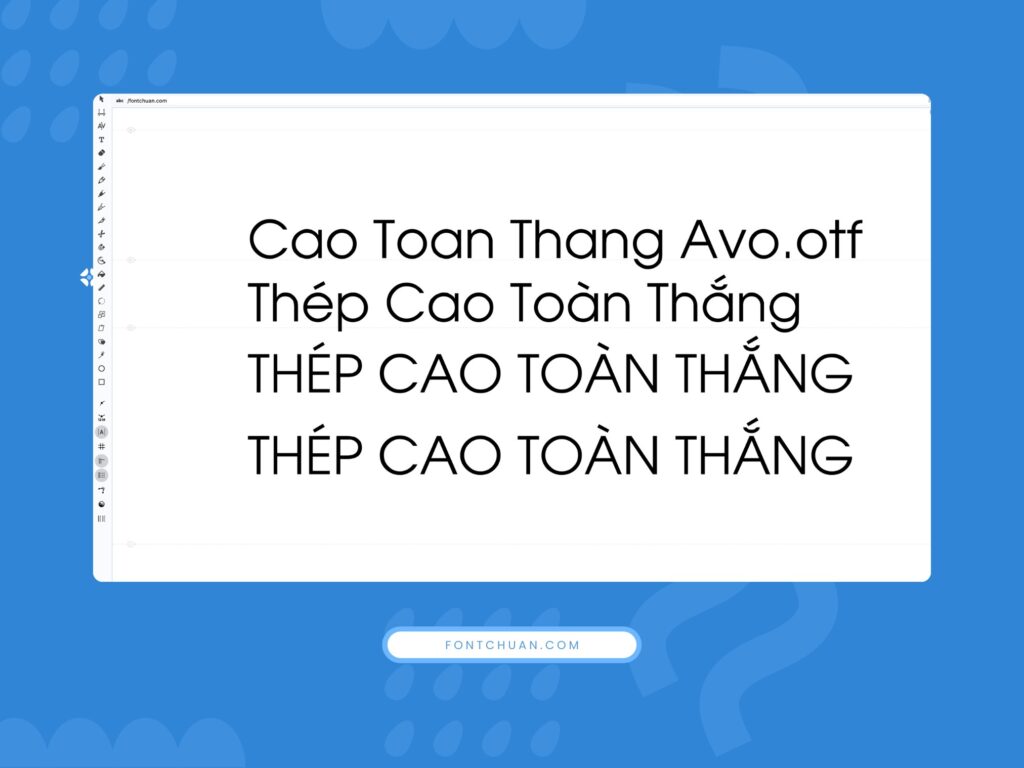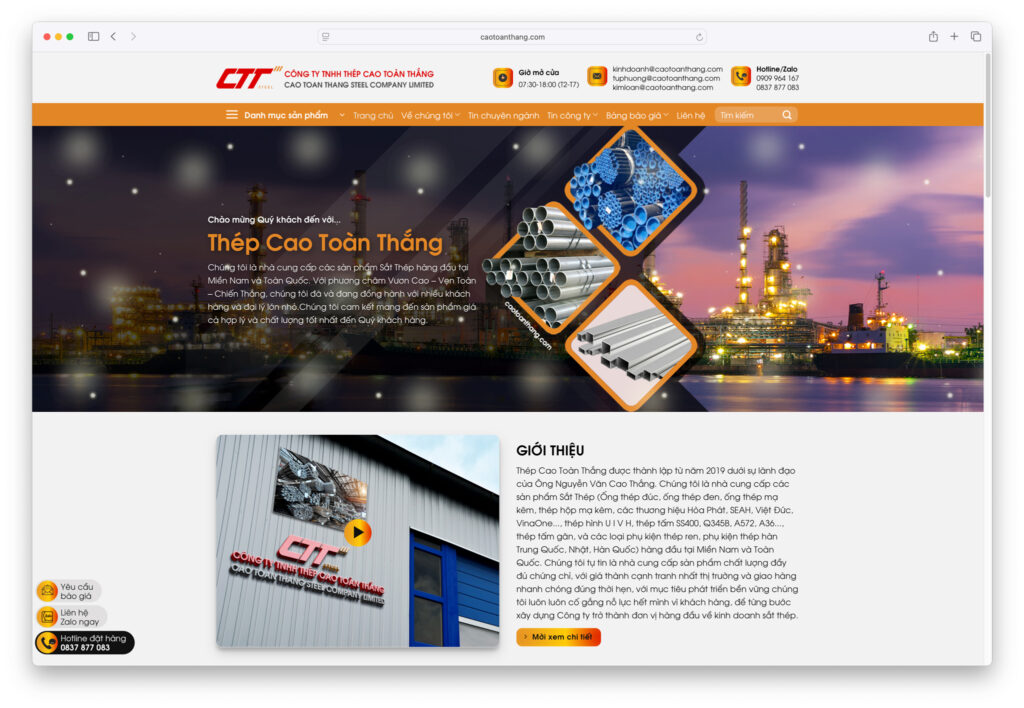
Thép Cao Toàn Thắng dẫn đầu “ngành thép” với Font riêng
Thép Cao Toàn Thắng dẫn đầu "ngành thép" với Font riêng
Thép Cao Toàn Thắng là một trong những đối tác và khách hàng chiến lược của Font Chuẩn. Một trong những doanh nghiệp uy tín hàng đầu trong lĩnh vực cung cấp sắt thép, đặc biệt là sản phẩm ống thép đúc tại Việt Nam. Với hệ thống sản phẩm đa dạng, chất lượng kiểm định rõ ràng, giá cả cạnh tranh và dịch vụ tận tâm, công ty đã xây dựng được mạng lưới khách hàng rộng khắp trên toàn quốc. Không chỉ chú trọng đến năng lực phân phối, Cao Toàn Thắng còn đầu tư bài bản vào hình ảnh thương hiệu để tạo nên sự khác biệt và tăng cường độ nhận diện.
Thách thức nhận diện thương hiệu trong ngành sắt thép
Ngành công nghiệp sắt thép mang tính kỹ thuật cao, với nhiều sản phẩm có hình thức và thông số gần giống nhau. Do đó, thương hiệu rất dễ bị đồng hóa nếu không có hệ thống nhận diện rõ ràng và nhất quán. Trong bối cảnh thị trường cạnh tranh gay gắt, việc đầu tư vào bộ nhận diện chuyên nghiệp không chỉ giúp tăng độ tin cậy mà còn tạo lợi thế rõ rệt về mặt truyền thông và tiếp cận khách hàng. Font chữ dù là một chi tiết nhỏ lại đóng vai trò trung tâm trong việc thiết kế các tài liệu, bảng hiệu, website và hệ thống bao bì sản phẩm.
Lý do chọn thiết kế font riêng tại Font Chuẩn
Thép Cao Toàn Thắng mong muốn sở hữu một kiểu chữ riêng biệt, phản ánh đúng tinh thần của ngành thép: mạnh mẽ, cứng cáp và hiện đại. Các font chữ phổ thông thường thiếu đi cá tính và không đáp ứng đủ yêu cầu về thẩm mỹ lẫn kỹ thuật của một doanh nghiệp công nghiệp. Vì vậy, việc thiết kế một bộ font chữ đẹp độc quyền là bước đi chiến lược nhằm đồng bộ hóa toàn bộ hệ thống truyền thông – từ bảng báo giá, website, bao bì đến nhãn mác thép.
Font Cao Toan Thang Avo.otf được thiết kế bởi Font Chuẩn
Font Cao Toan Thang Avo.otf ra đời
Font chữ “Cao Toan Thang Avo.otf” là sản phẩm được thiết kế riêng theo yêu cầu của doanh nghiệp. Font mang phong cách công nghiệp đặc trưng với các đường nét chắc khỏe, cấu trúc chữ hiện đại, tạo cảm giác vững chãi và đáng tin cậy. Toàn bộ hệ thống ký tự được Việt hóa đầy đủ, hỗ trợ in ấn rõ nét và trình chiếu tốt trên các nền tảng kỹ thuật số. Đây là yếu tố giúp doanh nghiệp thể hiện bản sắc riêng và dễ dàng mở rộng ứng dụng trong mọi hoạt động truyền thông.
Quy trình thiết kế và triển khai
Quá trình thiết kế font bắt đầu từ việc phân tích nhận diện thương hiệu hiện tại, ngành nghề hoạt động và mục tiêu truyền thông của doanh nghiệp. Từ đó, đội ngũ thiết kế đã phát triển các biến thể font phù hợp: cân bằng giữa yếu tố kỹ thuật và tính thẩm mỹ. Sau khi hoàn thiện, font được thử nghiệm trực tiếp trên các nền tảng thực tế như website, tài liệu nội bộ, bảng hiệu nhà máy, tem nhãn sản phẩm… trước khi chính thức đưa vào sử dụng.
Website CaoToanThang.com sử dụng Font Cao Toan Thang Avo.otf
Website CaoToanThang.com sử dụng Font Cao Toan Thang Avo.otf rất hoàn hảo
Kết quả và phản hồi tích cực
Sau khi áp dụng font “Cao Toan Thang Avo.otf” do Font Chuẩn thiết kế, bộ nhận diện của doanh nghiệp trở nên đồng bộ, chuyên nghiệp và dễ nhận diện hơn. Các tài liệu kỹ thuật, báo giá và ấn phẩm truyền thông đều trở nên rõ ràng, thẩm mỹ và nhất quán. Đối tác và khách hàng đánh giá cao sự đầu tư bài bản, từ chi tiết nhỏ nhất như kiểu chữ cho đến cách trình bày tổng thể. Đây cũng là bước đệm quan trọng giúp doanh nghiệp mở rộng quy mô và nâng cao vị thế trên thị trường.
Thiết kế font riêng không chỉ là yếu tố thẩm mỹ, mà còn là tài sản chiến lược giúp doanh nghiệp xây dựng thương hiệu mạnh mẽ và nhất quán. Với bộ font “Cao Toan Thang Avo.otf”, Thép Cao Toàn Thắng đã khẳng định vị thế tiên phong trong việc ứng dụng thiết kế vào ngành công nghiệp nặng. Đây là hướng đi đáng tham khảo Font Chuẩn gợi ý cho các doanh nghiệp kỹ thuật và sản xuất đang tìm kiếm giải pháp nâng cao hình ảnh thương hiệu một cách bền vững.